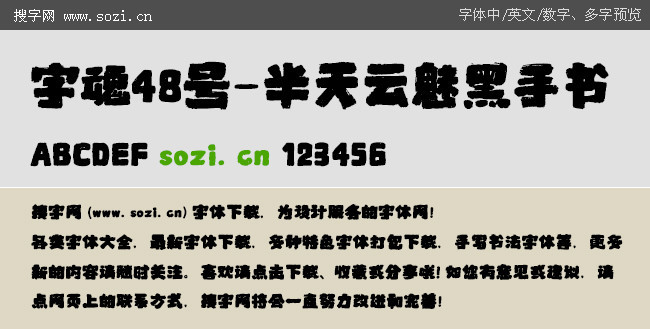
字魂48號-半天云魅黑手書
搜字網(wǎng)提供一款字魂48號-半天云魅黑手書中文字體下載,該字體是一款毛筆書法字體,該字體包含6763個中文、字母、 符號和數(shù)字,具有穩(wěn)重、復(fù)古、古典、力量 的風(fēng)格,可以滿足您設(shè)計上的各種需求,該字體主要用于活動展會、雜志、廣告、影視傳媒、青春校園、圖書、H5、活動 等場景。